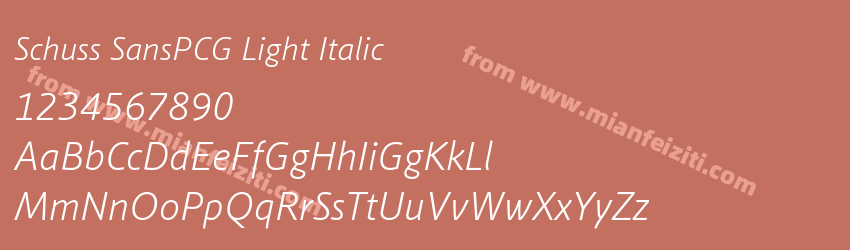
Schuss SansPCG Light Italic
字体名称: Schuss SansPCG Light Italic
Postscript名称: SchussSansPCG-LightItalic
本款“Schuss SansPCG Light Italic”是一款书写很新颖的字体,字体大方,适合各种设计作品使用!欢迎下载!